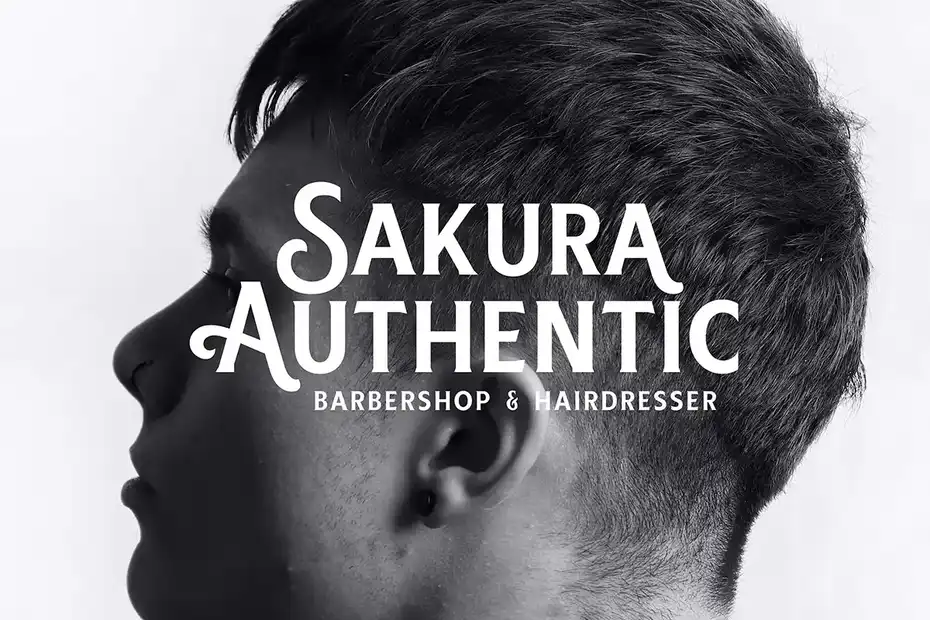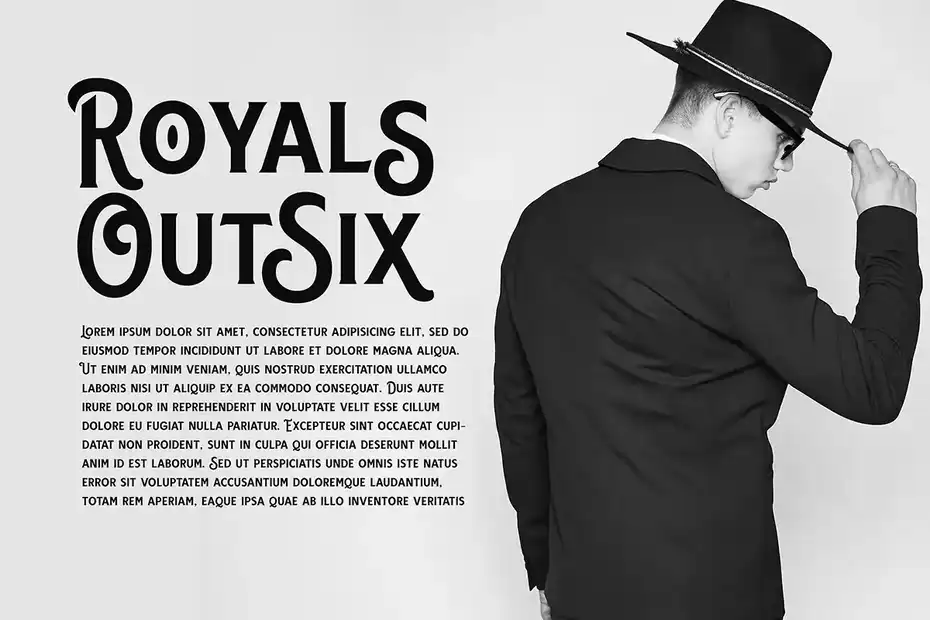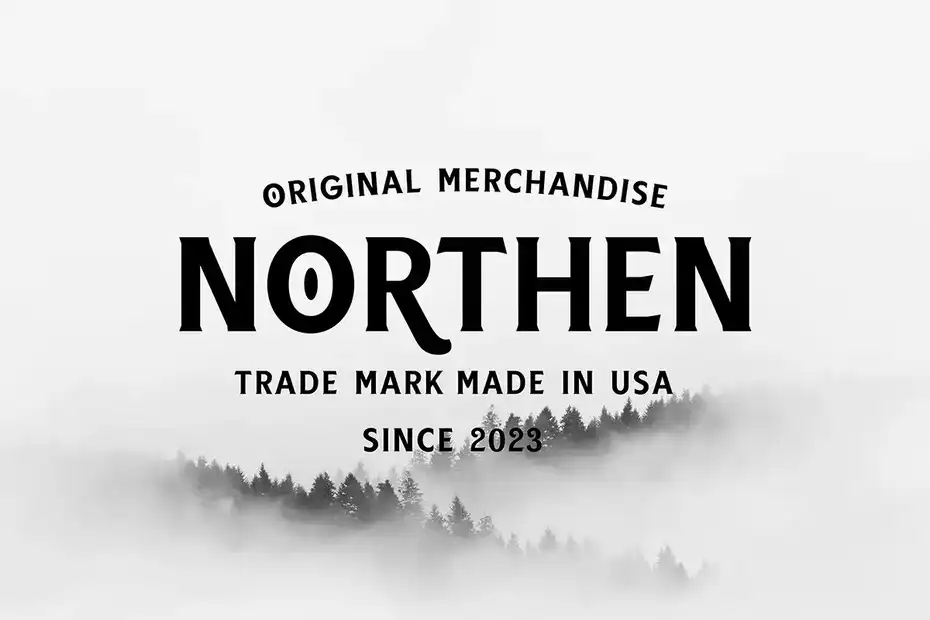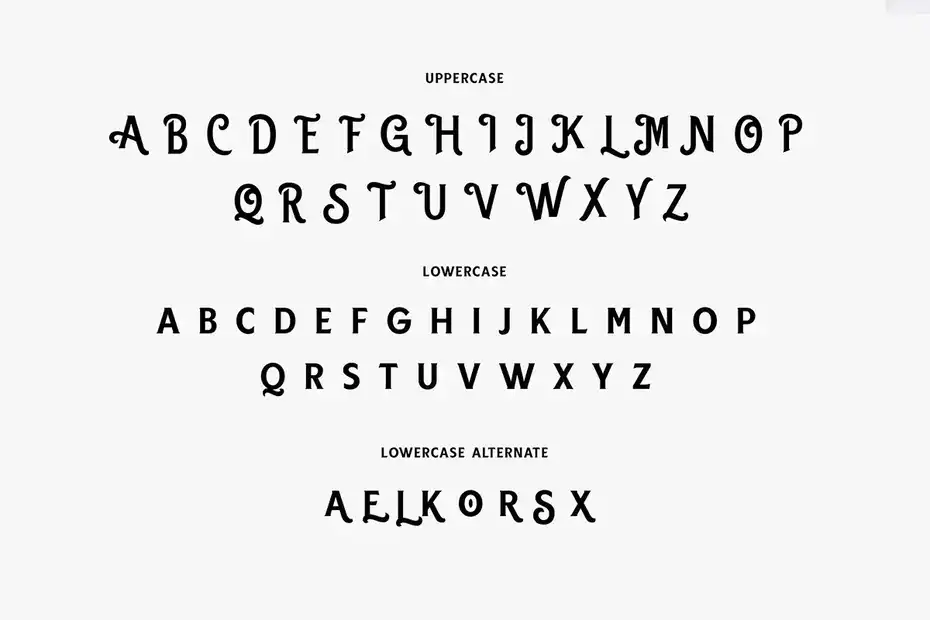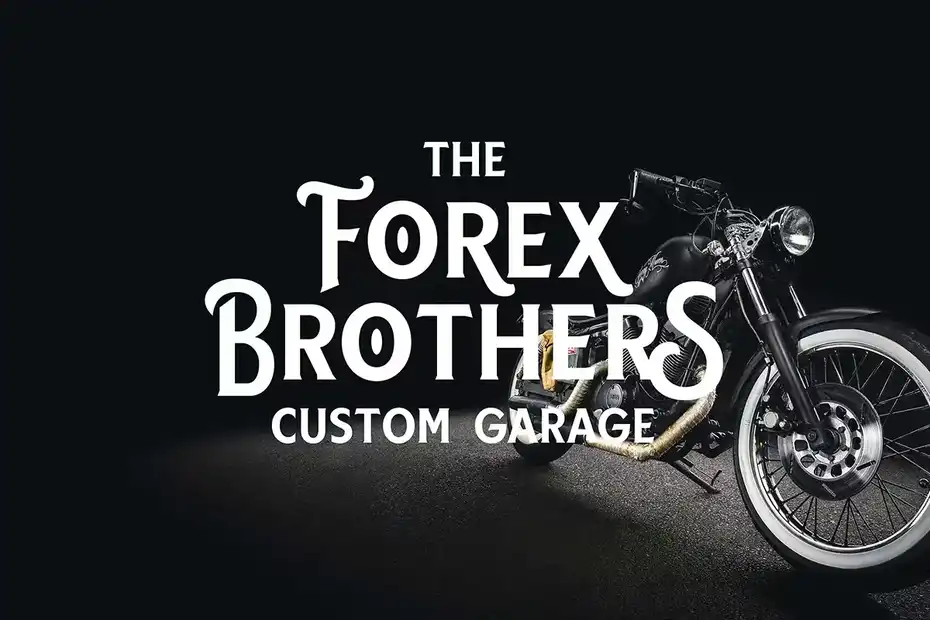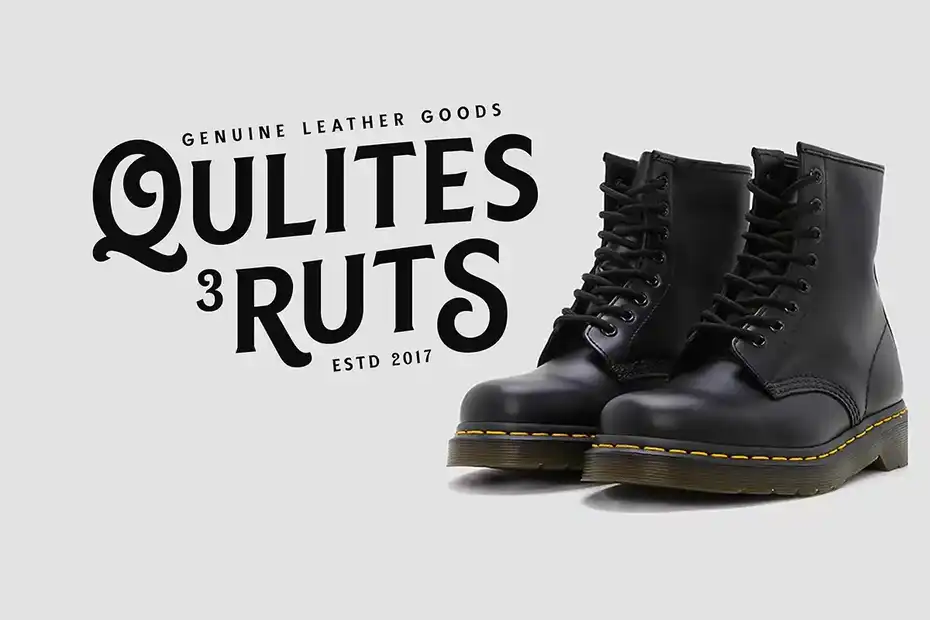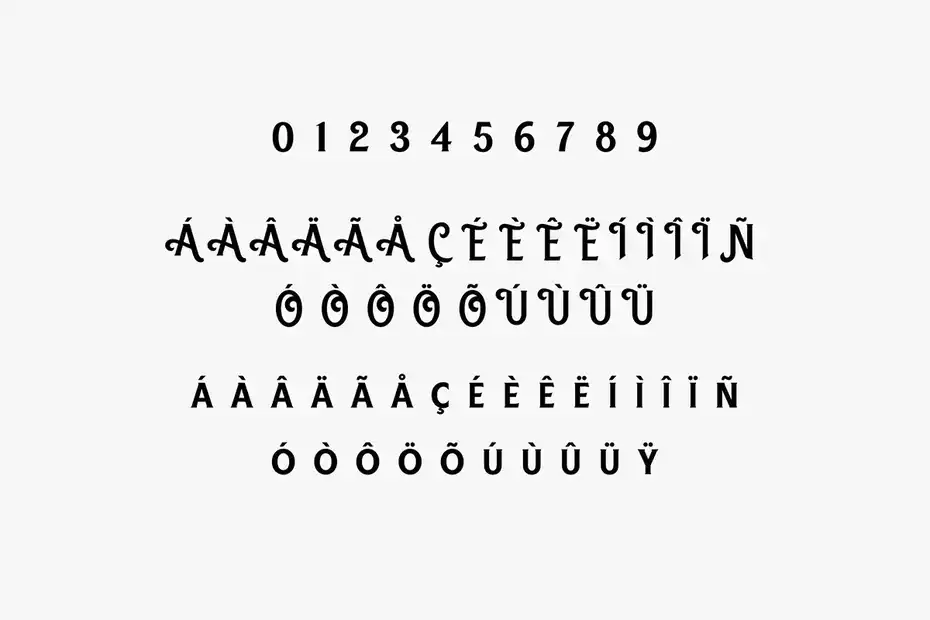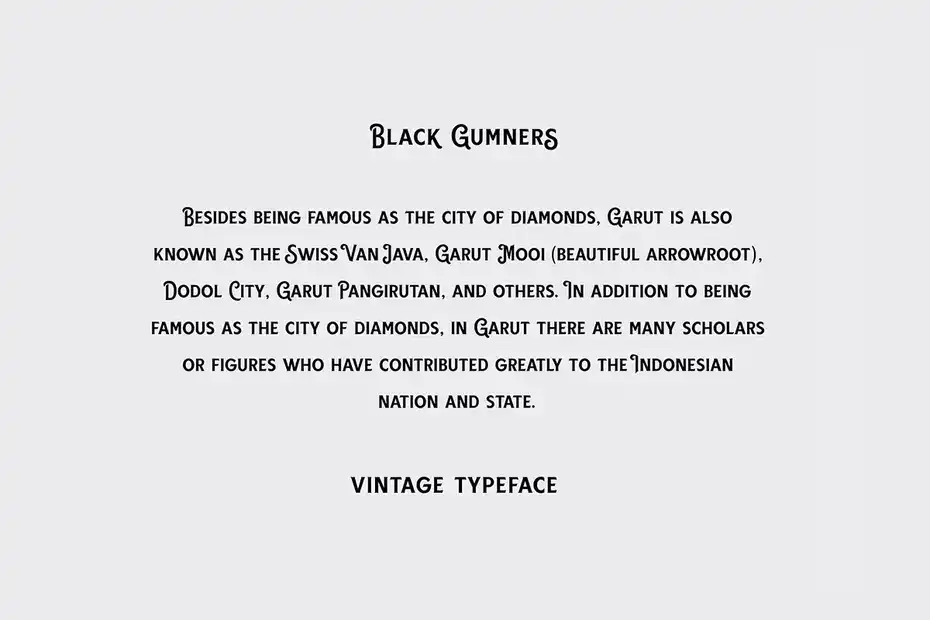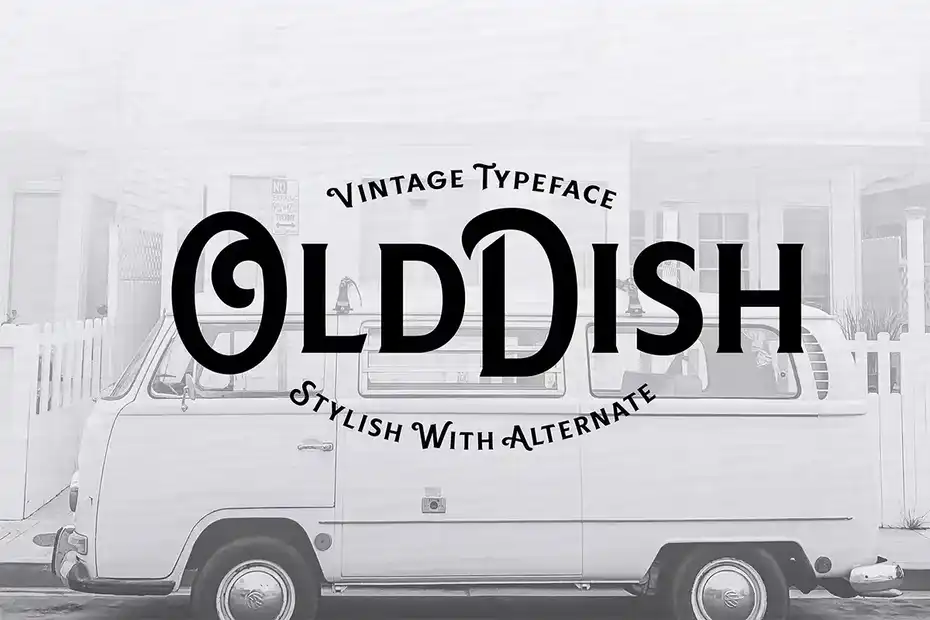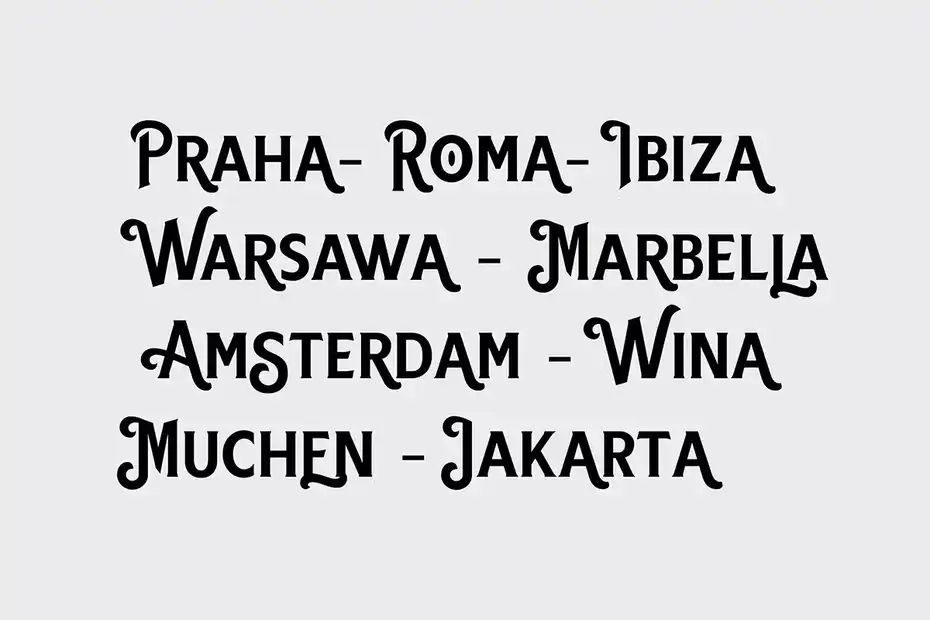
دانلود فونت انگلیسی Black Gumners Vintage Fonts
فونت انگلیسی Black Gumners Vintage Fonts : این مجموعه شامل یک فونت کلاسیک است که برای لوگو های کلاسیک، سربرگ و غیره مناسب میباشد.
• سبک: Serif